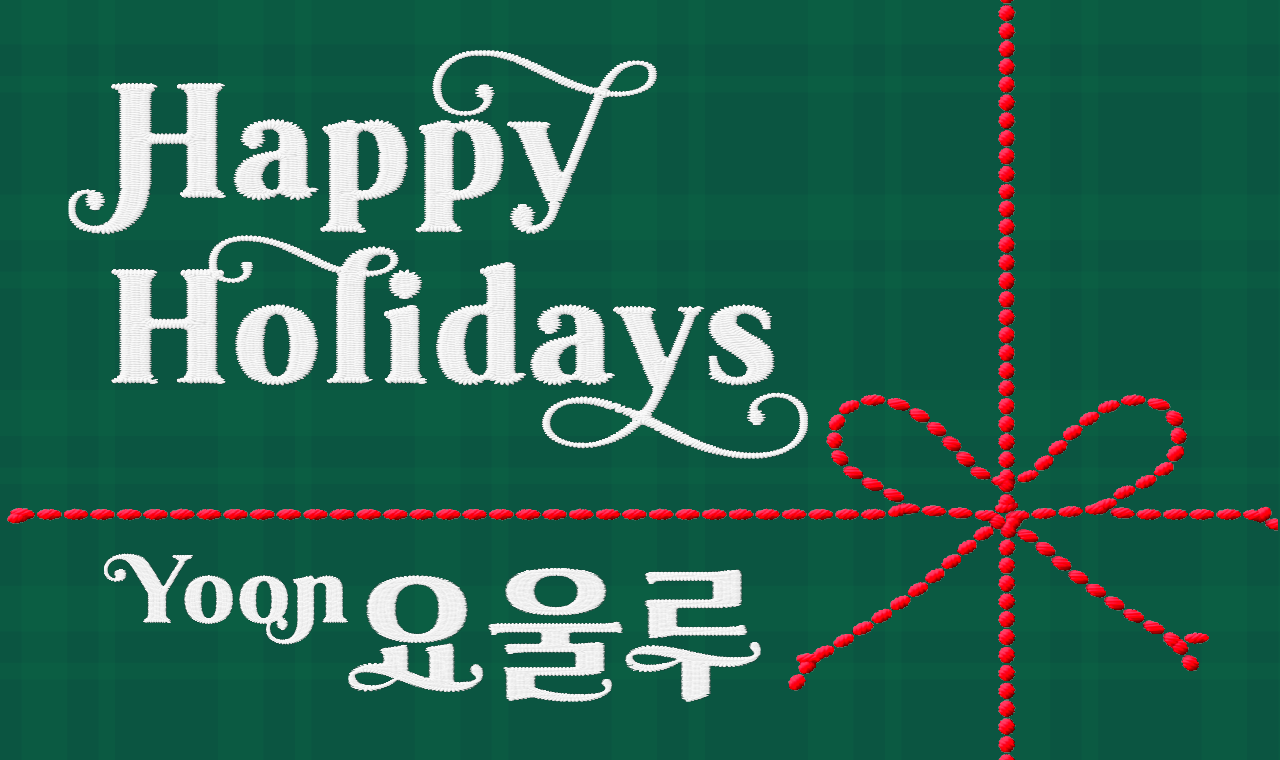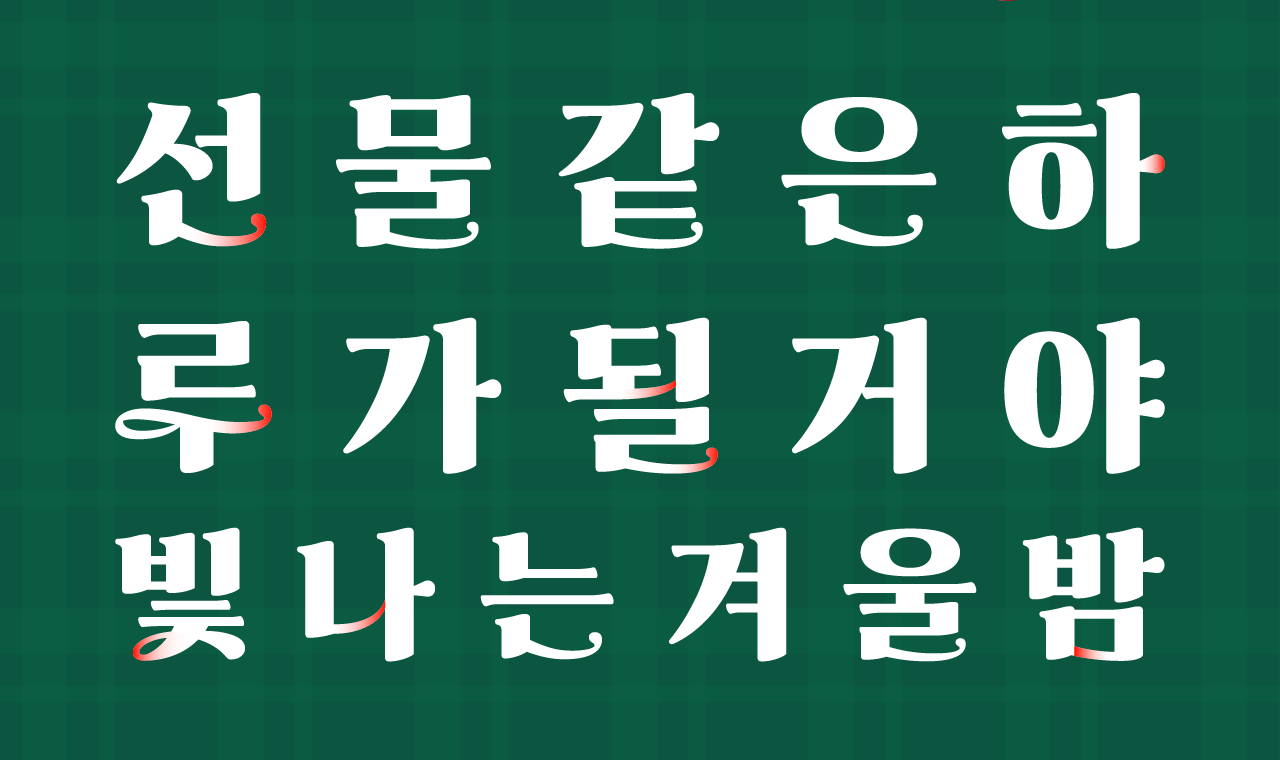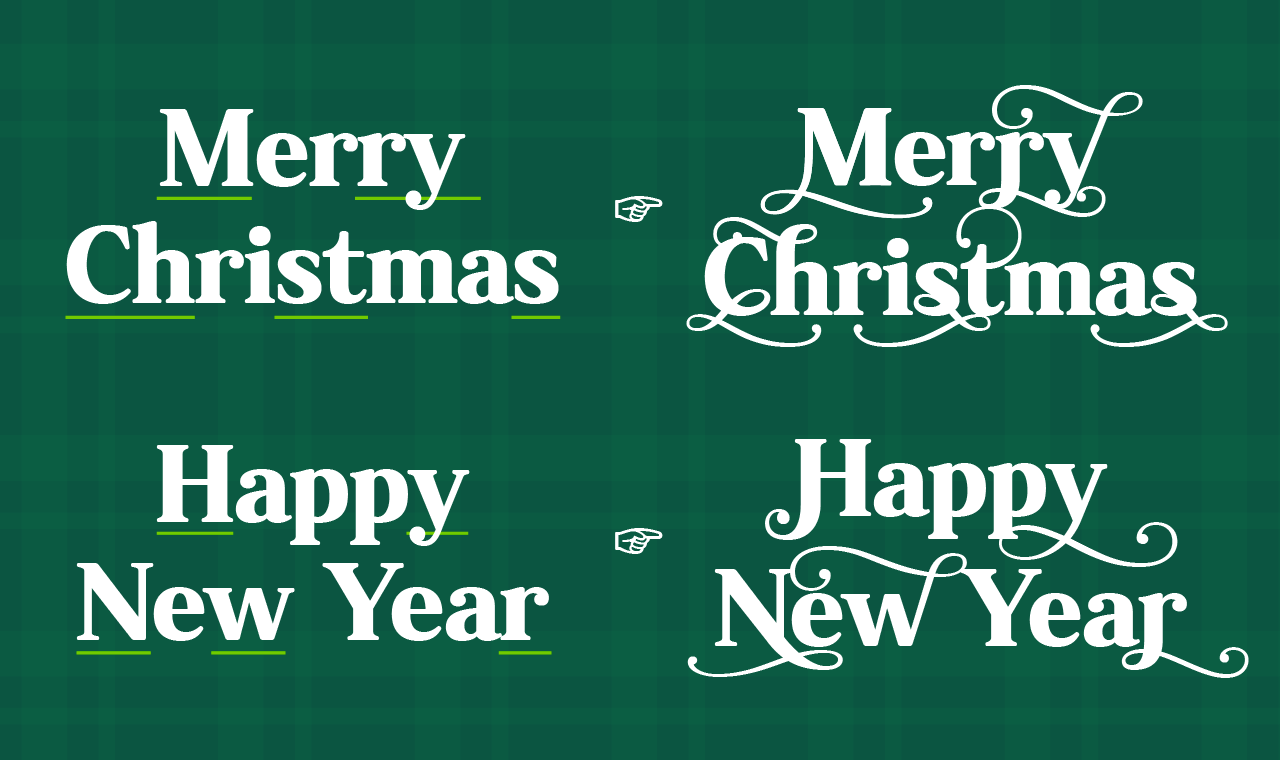
핀란드어로 크리스마스를 뜻하는 ‘요울루’는 설레는 겨울 풍경을 글자에 담은 서체입니다. 트리를 장식하는 둥근 오너먼트와 거리를 감싸는 반짝이는 전구들처럼, 획 끝마다 자리 잡은 유려한 곡선 장식이 요울루만의 가장 큰 조형적 특징입니다. 이러한 디자인 덕분에 화면 가득 빛망울이 맺힌 듯 화려하고 생동감 넘치는 분위기를 연출할 수 있죠. 크리스마스가 아니더라도 축하가 필요한 순간이라면 언제든 자유롭게 사용해 보세요. 경쾌한 글자들이 당신의 마음을 한층 더 즐겁게 전달해 줄 거예요!
Yoon 요울루